Cómo encontrar una fuente legible.
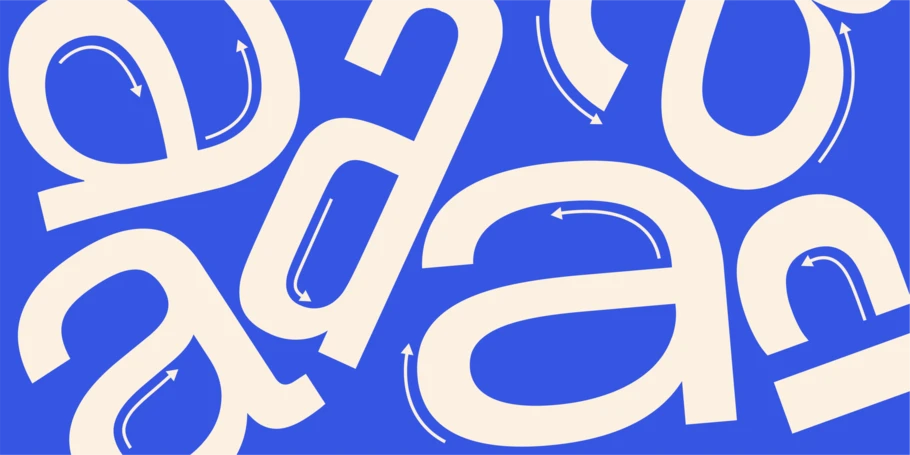
La legibilidad es un aspecto crucial que tener en cuenta a la hora de elegir una fuente para tu proyecto. Aquí te indicamos cómo encontrar una fuente legible que resulte cómoda para la vista de quien la lee
En Monotype recibimos muchas preguntas; pero una de las más habituales probablemente sea parecida a esta: ¿Cómo encuentro fuentes legibles? Es posible que se formule de manera diferente («¿cuáles son las fuentes más legibles?» o «¿cómo se puede saber si una fuente es legible?»), pero en definitiva se pregunta lo mismo: ¿qué hace que una fuente sea legible y cómo la encuentro?
Al igual que muchas preguntas sobre diseño, la respuesta a esta pregunta es una combinación de arte y ciencia, y está más influenciada por las mejores prácticas que por reglas estrictas. Lo importante es entender los componentes clave de una fuente que afectan a la legibilidad y, después, encontrar la fuente con esas características que mejor se adapte al lenguaje visual en el que estás trabajando.
La legibilidad es un tema amplio, con muchos más matices de los que podemos abarcar en un solo artículo, pero comprender algunos puntos clave te ayudará a elegir con seguridad una fuente legible para tu próximo proyecto. Vamos a ello.
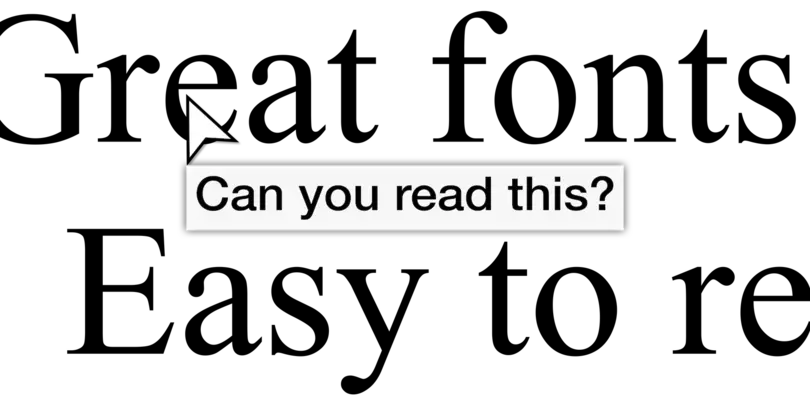
La legibilidad reside en la mente de la persona que lee.
Cuando leemos, nuestros ojos perciben las formas escritas en una página, traducen esas formas en letras y las combinan para formar palabras que luego asocian a sus significados. Todo eso pasa tan rápido que apenas nos damos cuenta.
Sin embargo, si uno de esos pasos en el proceso se ralentiza o encuentra un obstáculo, nuestra velocidad de lectura se ve afectada. Esto no importa en algunos casos (como un titular deliberadamente confuso en una revista); pero es muy importante en textos digitales o que deben captar la atención en un segundo, o bien en lecturas prolongadas con las que se pretende que el lector se sumerja en la historia.
En esencia, las fuentes legibles no deben molestar en absoluto a quien las lee. Deben reconocerse y comprenderse fácilmente para poder avanzar por las páginas de un libro con fluidez o identificar al instante el texto que se muestra en la pantalla de un coche. Leerlas tiene que resultar tan natural y sencillo como respirar.
¿Qué hace que una fuente sea legible?
Aquí la pregunta obvia es la siguiente: ¿qué hace que una fuente sea «agradable» para los ojos y el cerebro? Pero ¿las fuentes no son letras y ya está? ¿por qué hay letras más fáciles de leer que otras?
Al buscar fuentes legibles, es útil tener en cuenta las formas de las letras y las palabras (dato curioso: el término para designar la forma de las palabras es «bouma»). Tus ojos y tu cerebro en realidad no siguen cada curva y ángulo de una «a» minúscula antes de confirmar que es una «a» minúscula. Si acaso, ese era el proceso cuando estabas aprendiendo a leer. Aun así, la mayoría de las personas adquirimos la capacidad de determinar que una «a» es una «a» basándonos en su forma general y su relación con las letras que la rodean.
Dicho esto, las letras adoptan diversas formas dependiendo del estilo de un tipo de letra. La «O» de un tipo de letra de palo seco geométrica, como ITC Avant Garde, es un círculo casi perfecto. De entrada, la «ɑ» (alfa latina) podría confundirse con esa misma «o». ¿Puedes leer una letra de palo seco geométrica como Avant Garde o Futura? Por supuesto; pero podría ser más fácil.
Adentrémonos en el mundo de los tipos de letras humanistas. Estos tipos de letras se remontan a la tradición caligráfica y, por lo tanto, se caracterizan por presentar reminiscencias de la escritura a mano (de ahí el nombre). Un ejemplo popular de tipografía humanista es Proxima Nova, de Mark Simonson. Fíjate en la «o» y verás que es un sutil óvalo, no un círculo. Mira la «a» minúscula y observarás que los trazos de la parte inferior se vuelven más finos a medida que se encuentran con el trazo vertical. Todos estos detalles señalan la identidad de la letra al cerebro. Otros tipos de letras humanistas populares (y tipografías híbridas, entre humanistas y geométricas) son, por ejemplo, Frutiger, Morandi, Gotham y Optima.
Las fuentes con remate ofrecen una legibilidad similar al lector, por lo que no es de extrañar que sean la elección predominante para libros, revistas y otros contextos de lectura prolongada. Sin embargo, los tipos de letra con remate han planteado históricamente un desafío en entornos digitales debido al contraste de los trazos, que es la diferencia entre líneas gruesas y finas de un tipo de letra (lo analizaremos más adelante). Las fuentes con remate, un alto contraste de los trazos y líneas finas están destinadas a usarse en tamaños más grandes, mientras que las fuentes con remate diseñadas para tamaños más pequeños presentan un menor contraste. Este efecto y nivel de detalle a menudo se ven acentuados por la calidad de la pantalla, lo que hace que los tipos de letras con remate sean más difíciles de diseñar para textos digitales en los que se pueda necesitar una gama de tamaños. Por esto, los tipos de letras humanistas se convirtieron en la opción preferida para casos de uso digital y siguen siéndolo hoy en día, aunque las pantallas móviles modernas muestran fuentes con remate de una claridad casi perfecta.
Un ejemplo claro del polo opuesto a estos estilos es el tipo de letra Eurostile. Eurostile no tiene nada de malo; de hecho, es increíblemente popular en películas de ciencia ficción debido a su estética futurista (en los años 70) y retrofuturista (ahora). Cuando las empresas fabricantes de automóviles empezaron a incorporar pantallas táctiles y sistemas de infoentretenimiento en los vehículos, muchas decidieron usar Eurostile para la interfaz de usuario de dichos sistemas. Desafortunadamente, Eurostile se basa en gran medida en formas de letras cuadradas que pueden ser difíciles de distinguir entre sí cuando solo dispones de un instante para mirarlas, como cuando estás conduciendo un coche.
Características de una fuente legible.
Encontrar una fuente legible es como el cuento de Ricitos de Oro y, al final, el objetivo es encontrar una fuente cómoda de leer. Para los equipos de diseño, la clave está en entender algunos detalles esenciales que contribuyen a una buena legibilidad y, después, encontrar tipos de letra que aúnen esos factores con el lenguaje visual que buscas.
Contraste:
El contraste hace referencia a la diferencia entre los trazos gruesos y finos de una letra. Los tipos de letras con cierto contraste suelen ser más fáciles de leer porque la variedad de anchuras de los trazos ayuda al lector a distinguir las letras con formas similares.
Dicho esto, los tipos de letras con demasiado contraste pueden resultar bastante difíciles de leer fuera de los casos de uso de visualización. Una fuente como Bodoni, con su marcado contraste entre trazos gruesos y finos, da lugar a titulares impresionantes. Sin embargo, sus trazos finos prácticamente desaparecen en tamaños estándar de texto, lo que hace que el tipo de letra sea casi imposible de leer.
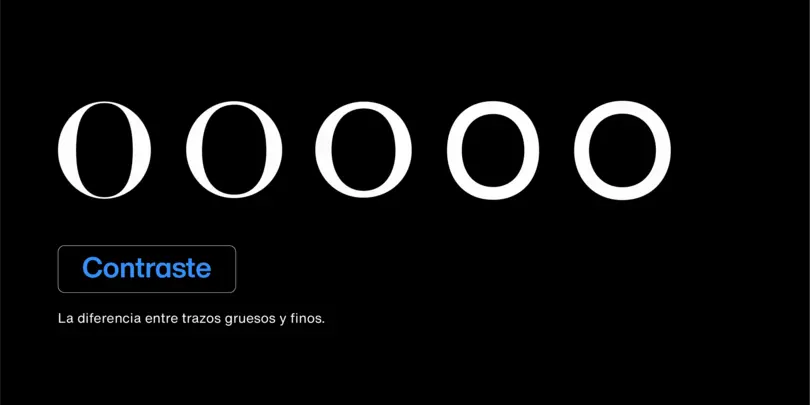
Ojo medio:
El ojo medio (o la altura de la x) hace referencia a la altura de la «x» minúscula de un tipo de letra, lo que básicamente determina la altura de todas las minúsculas de dicho tipo de letra. Los ojos medios más grandes tienden a ofrecer una mayor legibilidad, porque un tamaño más grande hace que las letras sean más fáciles de leer.
Sin embargo, si el ojo medio es demasiado alto, puede ser más difícil distinguir las mayúsculas de las minúsculas, e incluso diferenciar algunas minúsculas de otra (como la «h» y la «n»). Los ojos medios bajos también pueden proporcionar una buena legibilidad, dependiendo del diseño y peso del tipo de letra.
Espaciado, kerning y apiñamiento en general:
El espacio entre las letras es tan esencial para la legibilidad como las propias letras. Por ejemplo, una «r» y una «n» con un kerning inadecuado pueden parecer una «m». En general, un texto en el que las letras estén demasiado juntas puede ralentizar la lectura, mientras que un texto con las letras demasiado separadas puede dar la impresión de que se cae de la página.
Algunos tipos de letras tienen un espaciado y kerning bien pensados y requieren pocos retoques adicionales, pero muchas necesitarán ajustes al incorporarlas al diseño. Una tipografía legible debería transmitir fluidez y desahogo; debe guiar a quien lee por las palabras y frases sin necesidad de que tenga que leerlas dos veces.
Durante el proceso de descubrimiento, busca tipos de letra cuyas letras estén conectadas, pero no apiñadas y, si es posible, examina combinaciones de letras que puedan presentar problemas de kerning. Esto te ayudará a determinar los ajustes que tendrás que realizar por tu cuenta.
Tamaño óptico:
El tamaño óptico hace referencia a la práctica de diseñar diferentes versiones de una fuente teniendo en cuenta cómo y dónde se utilizará. Estas optimizaciones pueden incluir muchos de los aspectos mencionados anteriormente, como ajustar el espaciado, el ojo medio, el contraste de los trazos o los detalles. Los tamaños más grandes están diseñados para llamar la atención y usarse en títulos o incluso vallas publicitarias, y suelen resaltar los detalles y sutilezas de un tipo de letra, al tiempo que su espaciado es el apropiado para escalas más grandes. Por el contrario, las formas de las letras de fuentes de entre tres y siete puntos se han simplificado y exagerado para lograr una claridad óptima en esos tamaños pequeños, lo que permite una representación nítida en pantalla.
Aunque no todos los tipos de letras tienen tamaños ópticos, vale la pena buscarlas si tienes previsto utilizar la misma familia de fuentes en diversas aplicaciones y tamaños.
Los tamaños ópticos de Helvetica Now optimizan su uso en una amplia variedad de aplicaciones, desde carteles llamativos de gran tamaño hasta microtipografías hiperlegibles.
Cuando tengas dudas, pruébala.
Una vez que hayas investigado las opciones y hayas seleccionado tus favoritas, el paso más importante que puedes dar es probarlas. Cuando lo hagas, recuerda que existe una sutil diferencia entre legibilidad y facilidad de lectura; si la legibilidad implica poder distinguir entre los caracteres, la facilidad de lectura se refiere a la comodidad al leer. Si tienes un tipo de letra muy legible con un espaciado deficiente, no será muy fácil de leer. Como especialista en diseño, tienes la tarea de combinar el diseño tipográfico (el tipo de letra en sí) y la tipografía (cómo se usa) para dar con algo que resulte agradable de leer.
Así que escribe algo y comprueba si se lee cómodamente. ¿Hay una variación equilibrada entre letras altas y bajas? ¿Te parece que algunas palabras o combinaciones de letras están apretujadas? ¿Sientes la necesidad de volver atrás para leer las frases por segunda vez? Puedes incluso pedirle a amistades o colegas que lo lean también.
Una vez más, la legibilidad es una fusión de arte y ciencia, y sinceramente no existe ninguna fuente cuya legibilidad sea perfecta. Pero con algunas prácticas básicas recomendadas, sumadas a tu ojo y tus instintos, puedes encontrar algo que ofrezca una excelente legibilidad para tus lectores y usuarios. ¡Buena suerte!